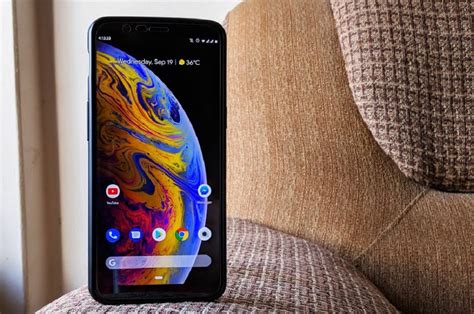
Ubah Font Android Jadi Mirip IPhone
Ubah Font Android Jadi Mirip iPhone: Panduan Lengkap
Halo guys! Pernah nggak sih kalian lihat tampilan font iPhone yang khas itu dan kepengen banget punya di HP Android kalian? Nah, kabar baiknya, mengganti font seperti iPhone di Android itu nggak sesulit yang dibayangkan, lho! Kalian bisa banget bikin HP kalian kelihatan stylish dan premium ala-ala iPhone tanpa harus keluar biaya mahal. Artikel ini bakal jadi panduan lengkap buat kalian yang penasaran dan pengen banget nyobain tampilan baru ini. Kita akan bahas tuntas step by step, mulai dari cara yang paling gampang sampai yang agak advanced dikit. Jadi, siapin diri kalian buat menyulap tampilan HP Android kalian jadi makin kece badai! Banyak banget lho manfaatnya kalau kalian bisa ganti font, nggak cuma soal gaya, tapi kadang font yang beda bisa bikin mata lebih nyaman baca, atau bahkan bikin notifikasi jadi lebih jelas terlihat. So, mari kita mulai petualangan mengubah font ini, guys! Dijamin deh, setelah baca ini, HP kalian bakal tampil beda dari yang lain, kayak punya aura-aura iPhone gitu. Nggak perlu lagi iri sama temen yang pakai iPhone, karena sekarang kalian juga bisa punya tampilan serupa, bahkan lebih keren lagi kalau kalian pintar ngopreknya. Siap-siap ya, dunia font menanti kalian!
Kenapa Sih Pengen Ganti Font Kayak iPhone?
Banyak banget alasan kenapa orang pengen banget punya font ala iPhone di HP Android . Pertama, tentu aja soal estetika. Font bawaan iPhone, terutama font San Francisco (SF Pro) yang mereka pakai, itu punya desain yang clean , modern, dan gampang dibaca. Tampilannya yang simpel tapi elegan bikin teks di layar jadi lebih enak dilihat. Nggak cuma itu, guys, font ini tuh kayak punya vibe premium gitu. Kalau kalian liat di Instagram, banyak banget influencer atau pengguna HP yang sengaja setting HP mereka biar kelihatan mirip iPhone, dan font ini jadi salah satu kunci utamanya. Selain bikin HP kelihatan mahal, font iPhone ini juga seringkali lebih enak dibaca dalam jangka waktu lama. Huruf-hurufnya itu didesain biar nggak bikin mata cepet capek, cocok banget buat kalian yang doyan baca artikel, chatting berjam-jam, atau bahkan nugas pakai HP. Bayangin aja, guys, kalian bisa dapatkan tampilan premium ini di HP Android kalian tanpa harus keluar uang buat beli iPhone. Keren banget, kan? Dan yang paling penting, ini nunjukin kreativitas kalian sebagai pengguna. Kalian nggak cuma terima apa adanya, tapi mau bereksperimen dan bikin HP kalian jadi unique . Ini juga bisa jadi cara buat nunjukin kepribadian kalian lewat tampilan HP. Kalau kalian suka yang simpel, modern, dan stylish , font ala iPhone ini pas banget buat kalian. Nggak heran deh, kalau banyak yang rela repot demi dapetin tampilan font ini di HP mereka. Jadi, kalau kalian ngerasa bosan sama font standar Android, atau pengen HP kalian kelihatan lebih up-to-date , mengganti font ke gaya iPhone ini bisa jadi solusi yang simple tapi impactful . Dijamin, HP kalian bakal langsung naik level penampilannya!
Metode Mengganti Font Seperti iPhone di Android
Oke, guys, sekarang kita masuk ke bagian paling seru: gimana caranya sih biar font di HP Android kita jadi mirip iPhone? Tenang, ada beberapa cara yang bisa kalian coba, tergantung tipe HP Android kalian dan seberapa dalam kalian mau oprek. Nggak semua cara butuh rooting , jadi jangan khawatir dulu ya! Kita akan bedah satu per satu.
1. Menggunakan Aplikasi Font Manager (Tanpa Root)
Ini adalah cara paling populer dan paling gampang buat sebagian besar pengguna Android. Cara ganti font seperti iPhone tanpa root ini biasanya memanfaatkan fitur bawaan HP atau aplikasi pihak ketiga yang canggih. Buat kalian yang pakai HP Samsung, Xiaomi, atau beberapa merek lain yang punya opsi ganti font bawaan, ini adalah jalur yang paling direkomendasikan. Kalian tinggal masuk ke pengaturan HP, cari opsi Tampilan ( Display ), lalu pilih Font. Di sana, biasanya ada pilihan untuk mengunduh font tambahan dari toko font bawaan produsen HP kalian. Nah, di toko font itu, kalian tinggal cari font yang mirip banget sama SF Pro-nya iPhone. Seringkali ada font gratisan yang desainnya udah mirip banget, tinggal diunduh dan diaplikasikan. Gampang banget, kan? Cuma beberapa klik aja.
Kalau HP kalian nggak punya opsi ganti font bawaan, atau pilihan fontnya terbatas, jangan sedih! Masih ada aplikasi font manager dari Play Store yang bisa jadi penyelamat. Beberapa aplikasi populer kayak iFont , HiFont , atau FontFix bisa kalian coba. Cara kerjanya mirip, kalian unduh aplikasinya, lalu cari font yang kalian mau di dalam aplikasi tersebut atau unduh file font dari sumber lain (biasanya file .ttf atau .otf ). Setelah itu, aplikasi ini akan bantu kalian mengaplikasikan font tersebut ke sistem HP kalian. Pro-tip : Cari font dengan nama yang mirip-mirip SF Pro, seperti ‘System Font’, ‘Default UI’, atau nama lain yang kesannya minimalis dan modern. Kadang ada font yang memang spesifik didesain buat meniru font iPhone, jadi tinggal cari aja.
Penting diingat : Meskipun cara ini tanpa root, kadang ada sedikit perbedaan di beberapa jenis HP. Ada juga kemungkinan tampilan font nggak 100% identik karena perbedaan rendering antar sistem operasi Android yang beragam. Tapi overall, cara ini udah cukup ampuh buat ngasih tampilan yang signifikan beda dan mirip banget sama gaya iPhone. Jadi, nggak perlu pusing lagi, langsung cobain aja aplikasi-aplikasi ini, guys!
2. Menggunakan Launcher (Tanpa Root)
Buat kalian yang pengen tampilan yang lebih menyeluruh alias nggak cuma font-nya aja yang berubah, tapi juga ikon aplikasi, homescreen layout , dan app drawer biar makin mirip iPhone, nah ini dia solusinya: pakai launcher! Ubah font Android seperti iPhone jadi makin gampang kalau kalian kombinasikan sama launcher yang emang didesain buat ngasih nuansa iOS. Launcher seperti Launcher iOS 16 , Phone 15 Launcher , atau sejenisnya ini bakal ngubah total tampilan HP kalian jadi kayak iPhone, lengkap dengan font yang mirip SF Pro.
Cara pakainya juga gampang banget, guys. Kalian tinggal unduh aja launcher pilihan kalian dari Google Play Store. Setelah terpasang, buka aplikasinya dan ikuti petunjuk setup-nya. Biasanya, launcher ini bakal minta izin buat jadi default launcher kalian. Setelah itu, voila ! Tampilan HP kalian langsung berubah drastis. Ikon-ikonnya bakal jadi kotak-kotak dengan sudut membulat khas iPhone, widget -nya juga bakal berubah, dan yang paling penting, font yang dipakai di homescreen dan menu-menunya juga bakal ikut berubah jadi mirip font iPhone. Kerennya lagi, banyak launcher ini yang udah pre-loaded dengan font SF Pro atau font yang sangat mirip, jadi kalian nggak perlu repot cari font lagi.
Keuntungan pakai launcher ini adalah kalian bisa dapatkan pengalaman pengguna yang mirip banget sama iPhone tanpa perlu melakukan perubahan sistem yang rumit. Kalau kalian bosan, tinggal uninstall launcher-nya dan HP kalian balik lagi ke tampilan semula. Fleksibel banget! Tapi perlu diingat juga, guys, kadang launcher ini butuh sumber daya HP yang lumayan besar, jadi kalau HP kalian speknya standar, mungkin bakal kerasa sedikit lebih berat. Tapi untuk sekadar nyobain tampilan, ini adalah cara yang super recommended dan efektif banget. Jadi, buat yang pengen full package nuansa iPhone, launcher jawabannya!
3. Menggunakan Custom ROM (Membutuhkan Root/Tingkat Lanjut)
Nah, ini dia cara paling advanced dan buat kalian yang emang suka ngoprek HP sampai ke akar-akarnya. Kalau kalian udah paham banget soal dunia Android dan mungkin HP kalian udah di- root , kalian bisa banget pakai custom ROM yang udah dibenamkan font ala iPhone. Custom ROM itu kayak sistem operasi Android yang udah dimodifikasi sama developer independen. Di dalamnya, banyak banget fitur tambahan yang nggak ada di ROM bawaan HP kalian, termasuk pilihan font yang lebih banyak dan bisa diubah sesuka hati.